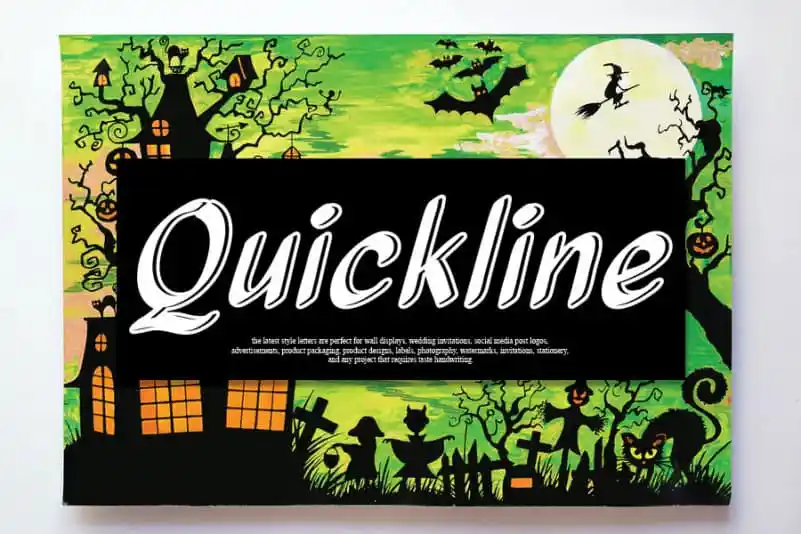
Quickline Script Font
Quickline Script Font é uma fonte feita à mão com traçados fluidos que capturam a delicadeza do estilo elegante. Esta fonte perfeita para seus projetos preferidos é ideal para adicionar um toque de beleza e unidade aos seus designs digitais. Seu formato levemente romântico não só reforça sua personalidade única, mas também dá vida a qualquer projeto que você lance sobre ela. Perfeito para criar designs memoráveis e atraentes, Quickline Script Font é a escolha perfeita para quem valoriza tanto a elegância quanto o toque único da mão humana. Seja seu próximo projeto uma carta de amor ou um poster de exposição, esta fonte adicional manterá tudo mais especial. Com o Quickline Script Font, você estará sempre conectado à arte do texto.